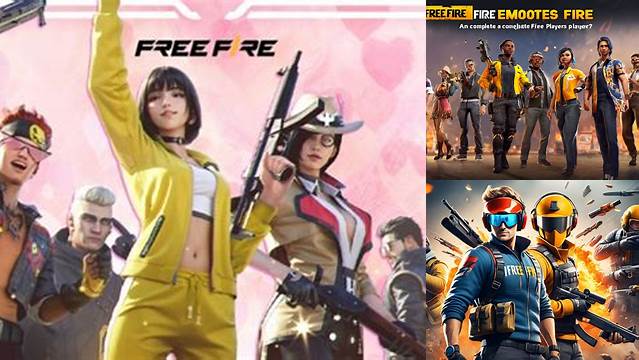
Font Free Fire: Panduan Lengkap Untuk Pemain
Free Fire, game battle royale populer, tidak hanya menawarkan aksi seru dan grafis memukau, tetapi juga perhatian terhadap detail yang mencakup penggunaan font. Pemahaman tentang nama font yang dipakai Free Fire dapat memperkaya pengalaman bermain dan membuka kemungkinan kreatif bagi para pemain. Mari kita telusuri seluk-beluk font Free Fire, mulai dari jenis yang digunakan, cara menemukannya, hingga bagaimana font ini berkontribusi pada identitas visual game.
Jenis-jenis Font yang Digunakan di Free Fire
Saat kita membahas nama font yang dipakai Free Fire, penting untuk mengetahui jenis-jenis font yang digunakan dalam game ini. Garena, pengembang Free Fire, menggunakan beberapa font berbeda untuk berbagai elemen visual. Tujuan utama dari penggunaan font ini adalah untuk menciptakan tampilan yang konsisten dan mudah dibaca, sekaligus mencerminkan tema futuristik dan penuh aksi yang menjadi ciri khas Free Fire. Font yang dipilih dengan cermat memainkan peran penting dalam menyampaikan informasi kepada pemain, mulai dari antarmuka pengguna (UI), notifikasi, hingga teks dalam game.
Beberapa font yang paling umum digunakan di Free Fire meliputi:
- Font UI: Font ini digunakan untuk semua teks yang muncul dalam antarmuka pengguna, seperti menu, pengaturan, dan informasi item. Font UI biasanya memiliki desain yang bersih dan mudah dibaca, bahkan dalam ukuran kecil. Contohnya adalah font Roboto atau varian serupa yang dikenal karena keterbacaannya yang tinggi dan tampilan modern.
- Font Judul dan Logo: Font yang digunakan untuk judul game, logo, dan elemen promosi lainnya sering kali lebih ekspresif dan menarik perhatian. Font ini bertujuan untuk menciptakan kesan visual yang kuat dan merepresentasikan identitas merek Free Fire. Font seperti Bebas Neue, Impact, atau font kustom yang dimodifikasi sering kali digunakan untuk tujuan ini, dengan karakter yang tebal dan berani untuk meningkatkan daya tarik visual.
- Font dalam Game: Untuk teks yang muncul selama permainan, seperti nama pemain, pesan obrolan, dan deskripsi item, font yang digunakan harus tetap mudah dibaca namun tetap selaras dengan estetika game. Font Roboto atau font sans-serif serupa sering dipilih karena kesederhanaan dan keterbacaannya. Kadang-kadang, font khusus yang dimodifikasi digunakan untuk menambahkan sentuhan unik pada teks dalam game, seperti memberikan efek visual atau menyesuaikannya agar sesuai dengan tema event tertentu.
Perlu dicatat bahwa penggunaan font dapat bervariasi tergantung pada pembaruan game, event khusus, atau perubahan desain visual. Garena terus berupaya menyempurnakan tampilan visual Free Fire, yang mungkin melibatkan perubahan pada font yang digunakan. Dengan memahami jenis-jenis font ini, pemain dapat lebih menghargai desain visual game dan mengidentifikasi font yang menarik bagi mereka.
Bagaimana Cara Menemukan dan Mengidentifikasi Font di Free Fire
Bagi pemain yang penasaran tentang nama font yang dipakai Free Fire dan ingin mengidentifikasi font tertentu, ada beberapa metode yang bisa digunakan. Mempelajari cara menemukan dan mengidentifikasi font ini bisa sangat berguna, terutama bagi mereka yang tertarik untuk membuat konten bertema Free Fire atau sekadar ingin memahami detail visual game.
Berikut adalah beberapa cara untuk menemukan dan mengidentifikasi font di Free Fire:
- Inspeksi Visual: Cara paling sederhana adalah dengan mengamati berbagai elemen visual dalam game. Perhatikan teks di UI, judul, logo, dan teks dalam game. Bandingkan karakter font dengan berbagai contoh font yang tersedia secara online. Situs web seperti WhatTheFont atau FontSquirrel menyediakan alat yang memungkinkan Anda mengunggah gambar teks dan mengidentifikasi font yang cocok.
- Alat Identifikasi Font Online: Gunakan alat identifikasi font online seperti WhatTheFont atau Fontspring Matcherator. Unggah tangkapan layar atau gambar teks dari Free Fire, dan alat ini akan mencoba mencocokkan font dengan database mereka. Alat-alat ini sering kali memberikan hasil yang akurat, tetapi kualitas gambar dan kejelasan teks sangat penting.
- Pengembang Web dan Desainer Grafis: Jika Anda memiliki akses ke alat pengembangan web atau desain grafis, Anda dapat menggunakan inspeksi elemen (inspect element) pada browser web untuk melihat informasi font yang digunakan pada elemen tertentu. Ini sangat berguna jika Anda sedang menganalisis tampilan situs web atau halaman promosi resmi Free Fire.
- Komunitas dan Forum: Bergabunglah dengan komunitas Free Fire, seperti forum, grup media sosial, atau saluran Discord. Tanyakan kepada pemain lain atau ahli desain grafis tentang font yang Anda cari. Komunitas sering kali memiliki informasi yang berguna dan dapat memberikan jawaban yang cepat dan akurat.
- Sumber Daya Resmi: Pantau sumber daya resmi Free Fire, seperti situs web resmi, blog, atau saluran media sosial. Garena kadang-kadang merilis informasi tentang desain visual dan font yang digunakan dalam game, terutama saat ada pembaruan atau event besar.
Dengan menggunakan metode ini, Anda dapat dengan mudah menemukan dan mengidentifikasi nama font yang dipakai Free Fire, memperdalam pemahaman Anda tentang desain visual game, dan memanfaatkan informasi ini untuk keperluan pribadi atau proyek kreatif.
Pengaruh Font terhadap Identitas Visual Free Fire
Nama font yang dipakai Free Fire tidak hanya berfungsi sebagai elemen dekoratif, tetapi juga berperan penting dalam membentuk identitas visual game. Pemilihan font yang tepat mencerminkan kepribadian merek, menyampaikan pesan kepada pemain, dan menciptakan pengalaman bermain yang lebih mendalam. Mari kita telaah bagaimana font berkontribusi pada identitas visual Free Fire.
- Mencerminkan Tema dan Genre: Font yang digunakan dalam Free Fire dipilih untuk mencerminkan tema futuristik, aksi, dan kompetisi yang menjadi ciri khas game. Font yang tebal, modern, dan mudah dibaca membantu menciptakan kesan visual yang kuat dan sesuai dengan genre battle royale.
- Membangun Konsistensi Merek: Penggunaan font yang konsisten di seluruh antarmuka pengguna, logo, dan materi promosi membantu membangun pengenalan merek dan kesan profesional. Pemain akan lebih mudah mengenali dan mengingat Free Fire jika elemen visual, termasuk font, konsisten di berbagai platform.
- Meningkatkan Keterbacaan dan Pengalaman Pengguna: Font yang dipilih dengan cermat memastikan bahwa teks di UI, notifikasi, dan teks dalam game mudah dibaca, bahkan dalam ukuran kecil. Hal ini meningkatkan pengalaman pengguna secara keseluruhan, memungkinkan pemain untuk memahami informasi dengan cepat dan efisien.
- Menciptakan Daya Tarik Visual: Font yang menarik dan unik dapat meningkatkan daya tarik visual game, membuat game lebih menarik dan menyenangkan untuk dilihat. Font dapat digunakan untuk menyoroti informasi penting, menciptakan efek visual, atau menambahkan sentuhan kreatif pada desain.
- Memperkuat Pesan dan Nilai: Font yang digunakan dapat menyampaikan pesan dan nilai-nilai tertentu yang terkait dengan game. Misalnya, font yang kuat dan berani dapat menyampaikan kesan kekuatan dan keberanian, sementara font yang lebih halus dapat menyampaikan kesan kehalusan dan kecanggihan.
Dengan memahami pengaruh font terhadap identitas visual Free Fire, pemain dapat lebih menghargai desain game, mengidentifikasi elemen visual yang menarik bagi mereka, dan bahkan terinspirasi untuk membuat konten bertema Free Fire yang kreatif dan efektif.
Kesimpulan: Merangkum Informasi Font di Free Fire
Secara keseluruhan, pembahasan tentang nama font yang dipakai Free Fire mengungkap aspek penting dari desain visual game yang seringkali luput dari perhatian pemain. Dari jenis-jenis font yang digunakan hingga cara mengidentifikasinya dan pengaruhnya terhadap identitas visual, font memainkan peran krusial dalam menciptakan pengalaman bermain yang menarik dan berkesan. Memahami font yang digunakan tidak hanya memperkaya pengetahuan pemain tentang game, tetapi juga membuka kemungkinan kreatif bagi mereka yang tertarik untuk membuat konten bertema Free Fire.
Dengan panduan ini, diharapkan pemain dapat lebih menghargai desain visual Free Fire, mengidentifikasi font yang menarik bagi mereka, dan memanfaatkan informasi ini untuk keperluan pribadi atau proyek kreatif. Jangan ragu untuk menjelajahi lebih lanjut, bereksperimen, dan berbagi pengetahuan Anda tentang font Free Fire dengan komunitas. Selamat bermain dan semoga panduan ini bermanfaat bagi Anda!